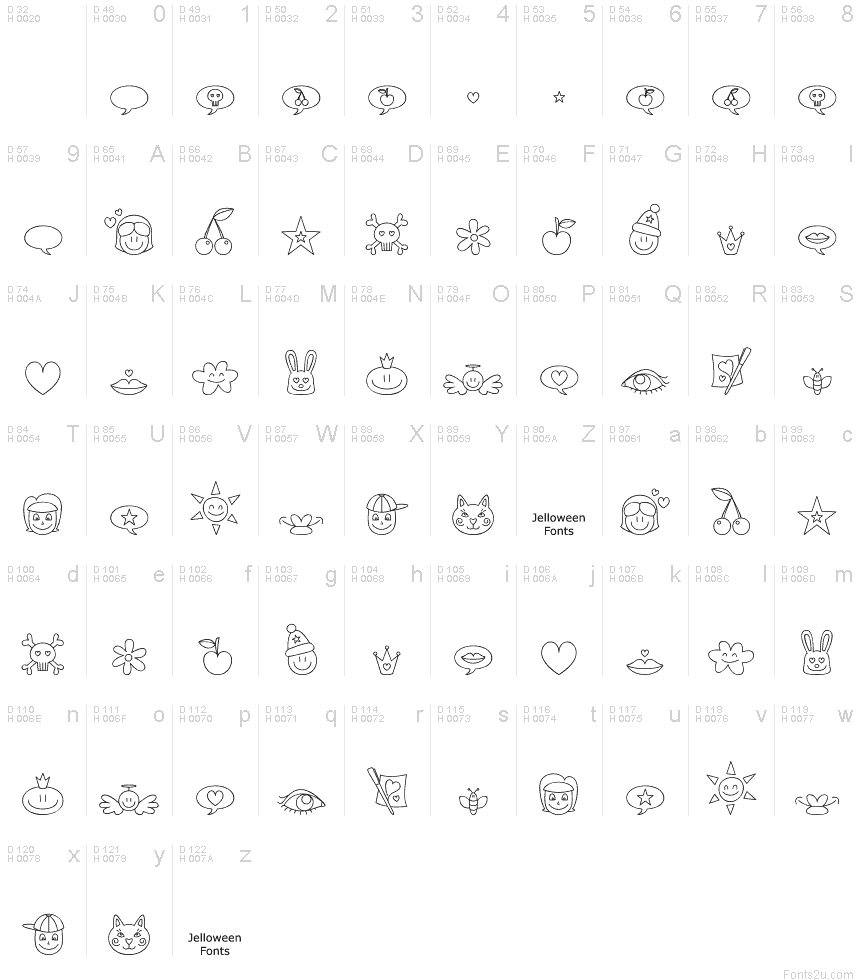
Jellodings من تصميم Tjarda Koster هو خط مجاني من نوع Dingbat بأسلوب الرسوم الكرتونية، مبني حول أيقونات لطيفة مرسومة باليد ذات طابع ناعم وودود. تعتمد المجموعة على الخطوط المستديرة والزخارف البسيطة المبتسمة — قلوب، زهور، أشكال أزهار منفوشة، وشخصية صغيرة بأجنحة — مما يجعل الانطباع العام مرحاً أكثر منه زخرفياً.
يناسب هذا الخط المجاني صفحات سجل القصاصات (Scrapbook)، ودعوات حفلات الأطفال، وأوراق الملصقات، وبطاقات المعايدة، والمواد المدرسية، ورسومات التواصل الاجتماعي الخفيفة، حيث يمكن لبعض الرموز المبهجة أن توصل الرسالة. كما يعمل الخط بشكل جيد كزخارف بسيطة، أو شعارات بأسلوب الشارات (Badge)، أو عناوين قصيرة، لأن الرسومات بسيطة بما يكفي ليتم قراءتها كلفتات بصرية سريعة.